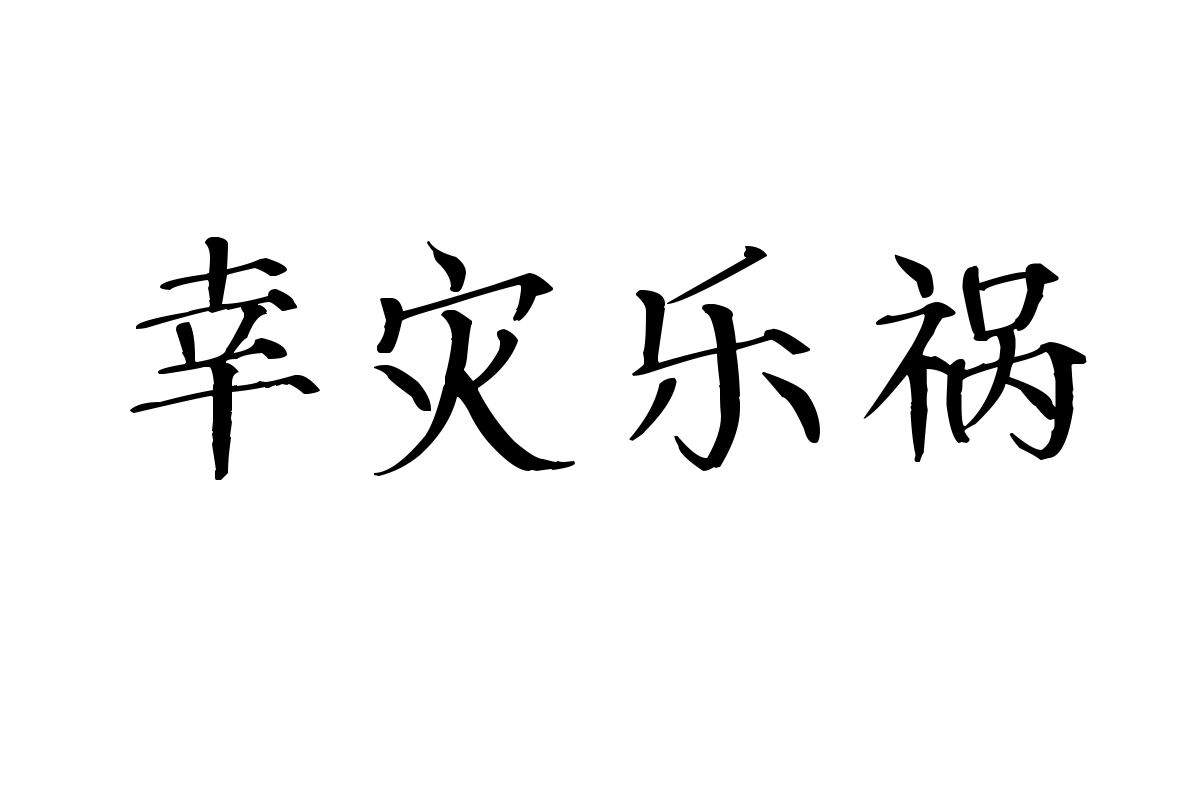
蝉羽吉力颜楷是一款具有独特风格的字体,它采用了传统的汉字书写方式,结合了现代设计元素,使得字体既有古典韵味又不失时尚感。这款字体的特点在于其笔画流畅、结构紧凑,给人一种简洁明了的感觉。同时,蝉羽吉力颜楷的字形也具有一定的艺术性,线条的粗细变化和笔触的力度都能够体现出不同的情感和意境。总的来说,蝉羽吉力颜楷是一款适合用于各种场合的字体,无论是用于文字排版还是艺术作品创作,都能够展现出独特的魅力。